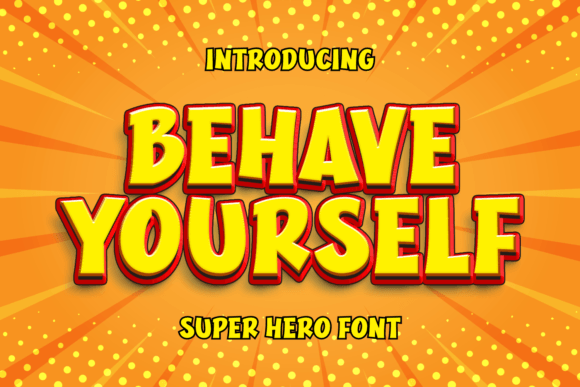
Behave Yourself
Die richtigen Designelemente zu finden, kann eine Herausforderung sein, aber Behave Yourself bietet eine außergewöhnliche Sammlung, die Ihre Arbeit sofort aufwertet.
Egal, ob Sie POD-Produkte (Print on Demand), Hochzeitseinladungen oder Social-Media-Grafiken erstellen, Behave Yourself ist die ideale Wahl.